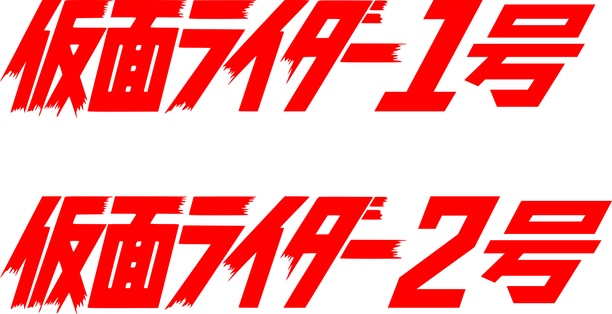
Font ini adalah hasil pembuatan ulang dari font yang muncul pada serial Kamen RIder Saber yang diproduksi oleh TOEI/Bandai
This font is a remake of the font that appeared in the Kamen RIder Saber series produced by TOEI/Bandai